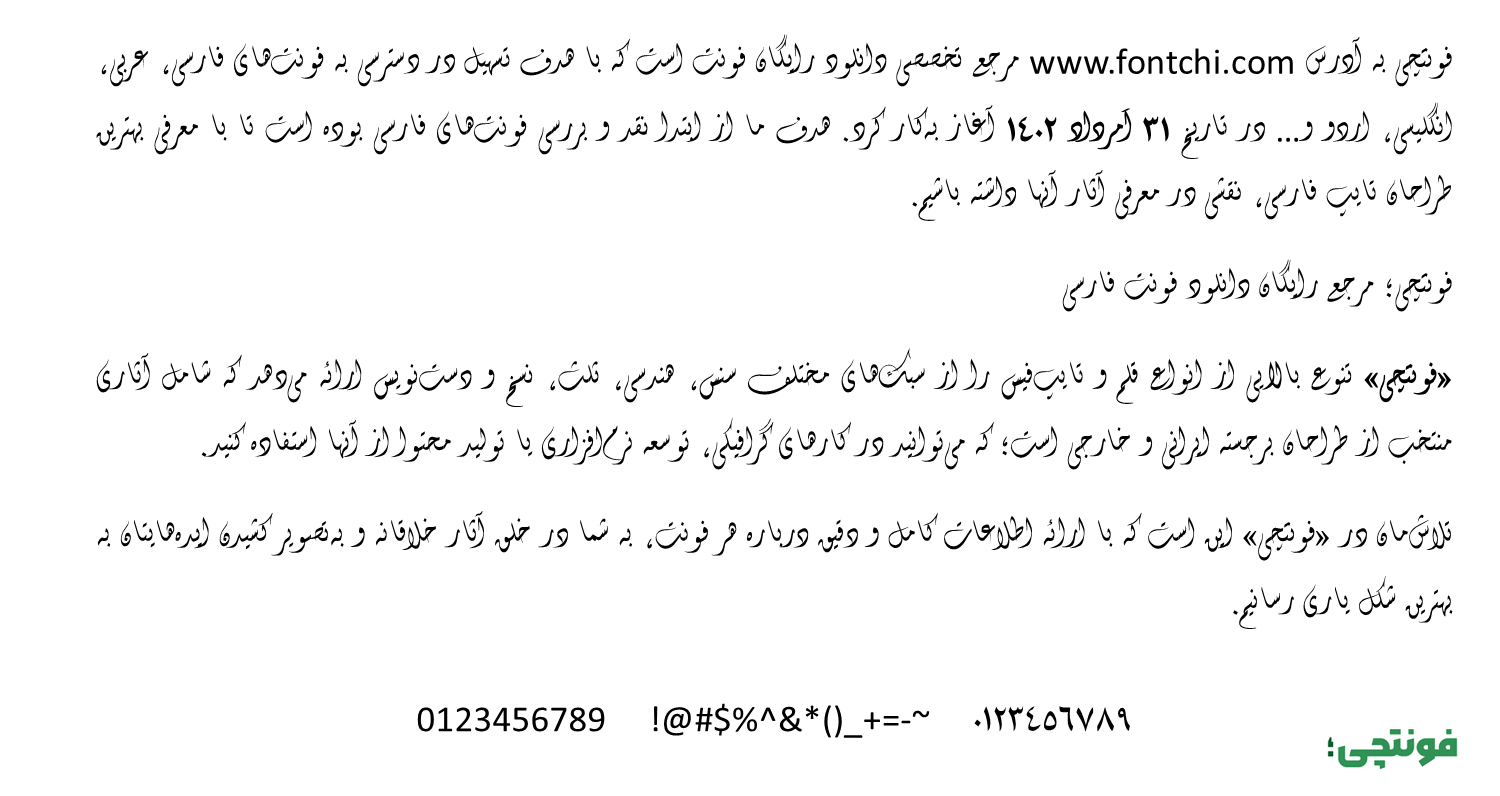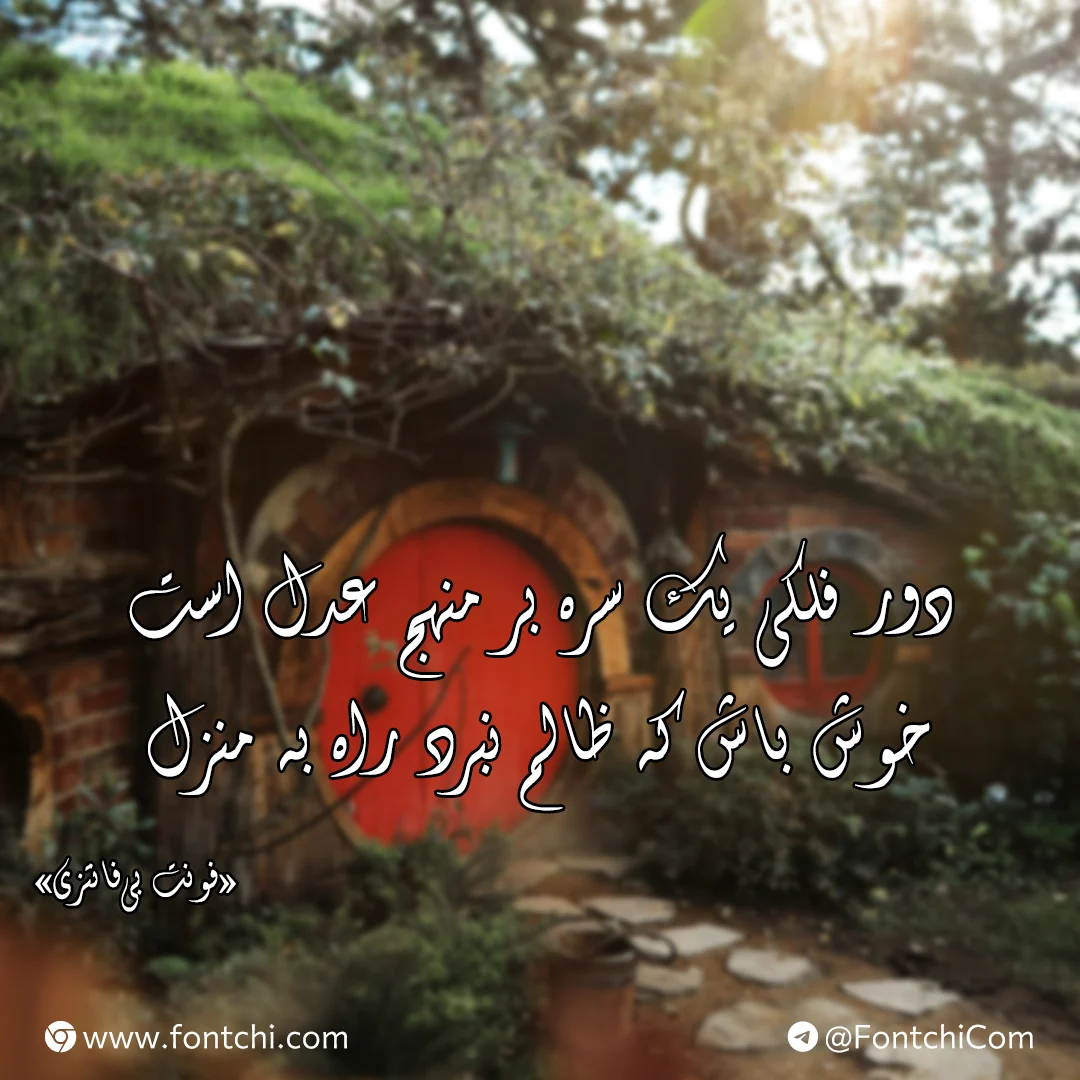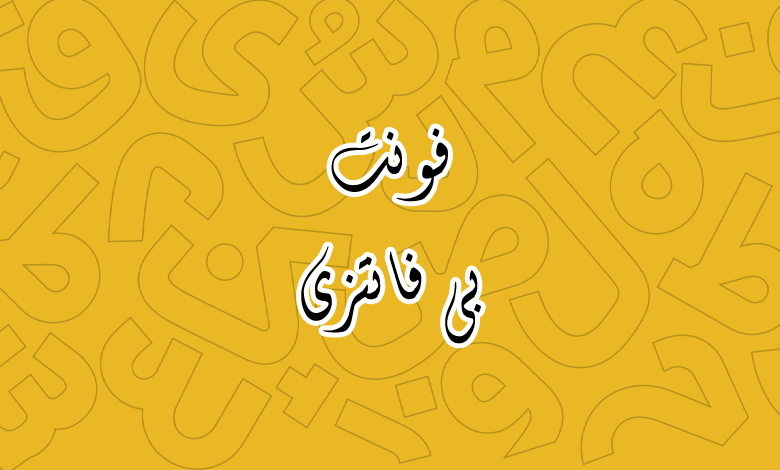
فونت بی فانتزی (B Fantezy)
| نام | بی فانتزی |
| نام نمایشی | B Fantezy |
| طراح | برنا رایانه |
فونت بی فانتزی (به انگلیسی: B Fantezy) از دیگر فونتهای آزاد طراحیشده توسط برنا رایانه است که در گروه فونتهای فانتزی قرار میگیرد. این فونت با طراحی خاص و منحصر به فردش، برای استفاده در پروژههای گرافیکی با جنبه نمایشی مناسب است. در ادامه با دانلود فونت بی فانتزی با شما همراه هستیم.
ظاهر فانتزی این فونت به گونهای است که برای استفاده در متون طولانی شاید انتخاب خوبی نباشد. خصوصا اینکه دارای یک وزن معمولی و نازک است که در متون طولانی خوانایی لازم را ندارد. از طرفی فونتهایی با این سبک طراحی که در تصویر زیر پیشنمایش آن را میبینید، برای استفاده در متون کوتاه و عناوین مناسب هستند.
فونت فارسی بی فانتزی با خطوط و انحناهای خاص خود، ظاهری فانتزی و جذاب دارد که میتواند توجه مخاطبان را جلب کند. از این فونت میتوانید در پروژههایی که نیاز به تایپوگرافی متفاوت دارند استفاده کنید.
گلیفهای این فونت فانتزی پشتیبانی کاملی از زبان فارسی و عربی را دارند. بهطوریکه حروف متفاوت عربی شامل «ك، ي، ة، ؤ، ئ» در آن قرار داده شده تا در پروژههای چند زبانه، مجبور به استفاده از فونت جایگزین نباشید. اما تنها یک کاستی در بخش اعداد وجود دارد که برای هر دو زبان مشترکا از اعداد عربی «٠٤٥٦» استفاده شده است.
فونت B Fantezy فاقد طراحی اختصاصی برای زبان انگلیسی است و در زبانهای لاتین از قلم پیشفرض سیستم عامل در این فونت استفاده خواهد شد. لذا برای زبانهای لاتین نیاز به فونتی نزدیک به این ساختار خواهید داشت.
این فونت دارای فرمهایی با انحناهای نرم و حرکتهای آزاد است که حس طبیعی دستنویس را تداعی میکند. با اینکه ویژگیهای کلاسیک و خوشنویسی سنتی را دارد، اما بهدلیل سبک آزاد خود، حس مدرنیته و فانتزی نیز در آن دیده میشود.
این فونت بیشتر برای طراحیهای گرافیکی، جلد کتاب، پوسترهای تبلیغاتی، کارت پستال، لوگوهای خاص و عناوین خلاقانه پیشنهاد میشود.
یکی از کاربردهای این فونت میتواند در پروژههای خلاقانه سایت مانند ساخت ابزارهای سرگرمی باشد یا اینکه بخواهید در سایتهای فرهنگی و هنری از این قلم برای بخشهایی همچون اسلایدر تصاویر بهره ببرید.